原标题:他们让奥运图标真正动起来了:走近设计师广村正彰与井口皓太
随着 2020 年东京奥运会及残奥会的临近,东京奥运组委会正式公布了将于运动会项目中使用的73个全新动态图标。这是自 1964 年首次引入静态图标后,东京再度首次成为引入动态图标的奥运城市。这组图标也显露出日本设计在全球范围内的顶级水平,图形设计者是日本设计师广村正彰(Masaaki Hiromura),让它们动起来的是井口皓太(Kota Iguchi)。
业内人士评价说,本次设计“巧妙地传达每项运动的特点和运动精神,同时艺术地突出运动员的活力”。体现了日本设计艺术的独特美学,将抽象主义与现实主义完美融合,并展示了广村正彰以及井口皓太两位著名日本设计师的个人风格。
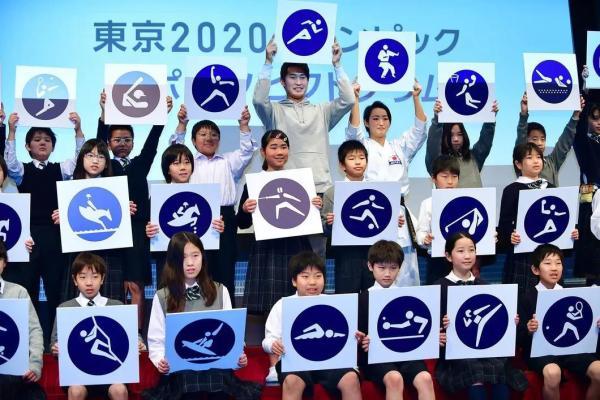
2020 年东京奥运会及残奥会动态图标公布
2020的设计,以1964年为原点
1964年,以设计评论家胜见胜(Katsumi Masaru)为中心,11位平面设计师制作的东京1964奥林匹克运动会运动图标,这套让全世界无论哪种语系的人都能够理解的图标,也成为奥运会历史上首次引入竞技图标。
当时奥运会首次在亚洲国家举行,沟通的隔阂不可避免,且就拉丁语系国家而言每一项赛事也会出现多种拼法,为了解决这一问题,1964年的东京奥运开创了一套人人能懂的视觉语言系统,在此后的奥运会中,赛事符号与奥运五环、燃烧火炬等共同纳入了奥运会的符号设计中。
1964年东京奥运会首次引入竞技图标
当时胜见胜及其团队从奥地利人奥图·纽拉特(Otto Neurath)和吉雨德·阿恩茨(Gerd Arntz)的作品中题取灵感,纽拉特是著名的是科学家和社会学家,他在1920年末至1930年初,他和视觉团队共同开放了一套图像语言,称为国际文字图像系统(Isotype),其背后的原则是创建视觉语言,利用图像形式反映社会、科技、生物、历史等资讯与关联性。
阿恩茨是“国际文字图像系统”的主导设计师之一,身为木刻艺术家和插画家,阿恩茨所做的简单的几何图像对平面设计的发展有着长远的影响。日本设计师胜见胜将阿恩茨的图像原理用于1964年的东京奥运,并提出简洁一致的设计框架,在展现摩登、便捷日本的同时,力求做到“简单美观,人人理解”,同时为未来奥运会主办方提供优质创新的基准。
奥地利人奥图·纽拉特和吉雨德·阿恩茨开发设计的国际文字图像系统。
2020年的设计,在继承1964年信息传达的基础上,融入了将跃动的运动员的美丽形态提炼的设计。通过这样的方式,也让图标给大会增添了一部分的装饰功能。
“上辈留存的设计(指1964 年的竞技图标)是一笔伟大的遗产”,广村正彰说道,“设计要与时代共进,所以我尝试融入运动员的活力,用青春的代表——肌肉,极简现代设计风格组成这套新图标。”而设计这套静态图标,广村正彰和他的团队花费了近两年的时间。并于2019年3月正式公布,后由动态设计师井口皓太接手制作动画效果,又历时了一年,最终完成。
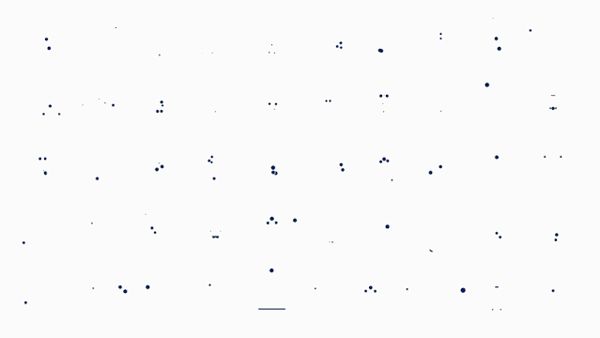
50个奥运会图标设计
目前公布的图标先以碎片的形式、从白色背景中出现,再完成运动动作后又以碎片化形式消失,回到最初的空白帧,让人意犹未尽。
在组委会发行的短片中,对动画的一些亮点进行了更深入的探讨,比如射箭运动员拉弓、篮球运动员扣篮、体操运动员站立劈腿等等。每一个图标都是用最简单的图形元素组成:肢体和圆形的头象征着运动员以及他们的运动器材,加上特殊动态效果,如同一个球,嗖地一声把能量感带入进了图标整体动态过程中。组委会表示这些动态图标可以“在二维空间中再现运动员的三维运动,并能表现出更多动态动作,如扭转。”
2020东京奥运会空手道项目标识
此次设计的图标分为无框型与有框型两种,颜色也只选用蓝白两个色系,主色蓝色源于2020奥运会会徽,这也是日本国家队的代表色系。
2020东京奥运会竞技体操图标的演变
广村正彰:最理想的标识系统就是没有标识
广村正彰1954年出生,毕业于素有“东京五美大”之称的武藏野美术大学,其校友更囊括了原研哉、奈良美智、桥本奈奈未等在设计、艺术领域极具有代表性的人物。随后广村亦于日本极具代表的设计师田中一光(Tanaka Ikko)的工作室参与工作,在 1998 年正式创办了 Hiromura Design。凭借众多出色的设计,广村正彰曾获纽约艺术指导协会年度奖、新加坡设计奖 、日本 JCD 商业空间设计大奖等全球极具设计荣誉奖项。
在设计中,广村正彰主张思考信息和人之间的关系。他曾说:“思考信息是如何被传达比如何去传达信息更为重要,对于设计师而言,最重要的事情并非表达,而是去找出事物的本质。我始终在思考信息和人之间的关系。”
广村正彰为东京北千住一家餐厅做的字体设计
2004年,广村正彰为位于东京北千住一家餐厅做的字体设计在中国被作为一种典范。这项目设计中,每个相关食物的字体里都有一部分被食物的图形所代替,“鳗”字里带着鳗鱼、“量”字里有天平、“煮”下有火……即使是不识日文的外国人,甚至是孩子,也无需过多解释,便能了解其含义。
餐厅外墙上对于字体设计的运用。
广村正彰和他的工作室最为人熟知作品应当是“9小时胶囊旅馆”的标识系统设计。这项工作也延续至今,Hiromura Design网站显示,广村正彰工作室直至2018和2019年还分别完成了“新大阪9小时胶囊旅馆”和“水道桥9小时胶囊旅馆”(东京)的设计。比较之下,不难发现,随着时代的发展,一些设计细节在变化,但其设计理念却在时间中不断延续和升华。
9小时胶囊旅馆的标识系统设计
以“一小时梳洗,七小时睡眠,一小时休息”作为经营理念。广村正彰在“九小时胶囊旅馆”的导视系统中,选择极为简洁克制的视觉形态,精准呈现住宿场所需要的相关信息。他将咨询前台、索取房间钥匙、淋浴、进入胶囊房间,划分为四个步骤,以简明的图标表现在墙壁上。
在“新大阪”车站内,看到“
新大阪
9小时胶囊旅馆”的店招。2018年设计
东京“水道桥9小时胶囊旅馆”梳洗处,2019年的设计
此外,广村正彰曾负责日本科学未来馆,横须贺美术馆,铁路博物馆,墨田水族馆,东京站美术馆,名古屋城本丸御殿等的美术馆和展览的艺术指导和视觉设计工作。
横须贺美术馆外的广场
其中位于镰仓的横须贺美术馆可以看到海天之景,广村正彰的设计也因环境而生。他设计的树立在美术馆门口“海的广场”的门牌像是一面“海的镜子”,映照着由浅渐深的蓝色海天风景,并抽象成为由深浅两种蓝色组成的美术馆。而到了馆内,图书室、楼梯、寄物处甚至厕所,都有鲜明的标示指引,设计上也一別过去的既定形式,广村采用以“人”作为主题的识别,看书的人、打电话的人、上楼梯的人或者是抱奶瓶的人,像是过去洞穴壁面的象形文字般印附在简约的墙壁之上。
横须贺美术馆内的标识
广村正彰为水族馆展览“墨田水族馆×葛饰北斋”设计的海报,也被认为是现代设计与传统文化的偶遇。广村正彰提取葛饰北斋所绘制的鱼,与墨田水族馆的极简标识并列,借助湖蓝和桃红两色的印染与对比,似乎也在向观者抛出问题——现代化的墨田水族馆与江户时代画家葛饰北斋之间到底发生什么样的关联?
广村正彰为水族馆展览“墨田水族馆×葛饰北斋”设计的海报
简洁直观,又保持着极高的艺术魅力广村正彰设计的特点。他认为:“最理想的标识系统就是不需要任何标识,我希望它可以直达对方的脑海”。
广村正彰的其他设计
井口皓太:尝试传统文化与现代艺术融合
负责制作本次奥运会图标动态效果的井口皓太1984年出生于日本横滨,同样毕业于武藏野美术大学,作品包括了平面、影像、空间、网页等不同领域的设计,不断尝试传统文化与现代艺术的融合。
井口皓太
在他的众多设计中,一个名为“無限に続く道と漢字”系列的GIF动画别具匠心地将平面字形与立体空间相糅合,加入动画元素,空间的纵深感与无限循环所带来的哲思意味一览无余,不失为传统文化与现代艺术碰撞的一次很好的尝试。对于用汉字的中国人,这组设计可以获得最直接的理解。
“无限延续的汉字”中的竹
比如,“竹”是一个极富传统中华文化的汉字,设计师直接将“竹子”的实体意象挪用过来。用笔直挺立的竹节来具象化汉字中的竖笔画,而两撇笔画丿,则十分讨巧地化用了竹叶作为元素,整体取材于竹子,制成了“竹”字。且最后不忘在添加了红色的太阳标志,这一举动让这幅画面更具日式风格。
井口皓太作品《CI_clock PLST》
在井口皓太的设计网站上,记录了他和一些商业品牌的合作,其中也多显示出他对运动中的一切的关注,且有一些设计为NIKE、H&M、POLA所做,实为日常所见,只是未把这些设计和井口皓太联系起来。2015年,他还参与了米兰世博会日本国家馆“未来餐厅”的设计,参观者手拿筷子,在虚拟的互动装置上点菜、饮食。通过食物介绍日本文化。
井口皓太为米兰世博会日本馆“未来餐厅”中的字体设计。
2020东京奥运的动态图标,井口说他的团队花了一年多的时间来制作。“新的动态图标将通过其精美和更容易理解的表达方式,扩大每一项运动的吸引力”,井口说:“我希望它们能够照亮每一场赛事,作为2020年东京奥运会的创举,也希望它们能够作为未来奥运会的财产传承下去,并激励其他国家的视频设计师。”
2020东京奥运会田径项目标识
虽然,目前因为疫情的出现使得东京奥运会产生了一些不确定因素,虽然关于奥运会,安倍晋三一再表示,“将推进万全准备,使之成为对运动员及观众而言是安全、安心的大赛”。届时这些白底的自由型图标将用于海报、门票和许可产品,蓝圆型图标将用于地图、比赛场地标识、比赛指南和网站等更多的用途。